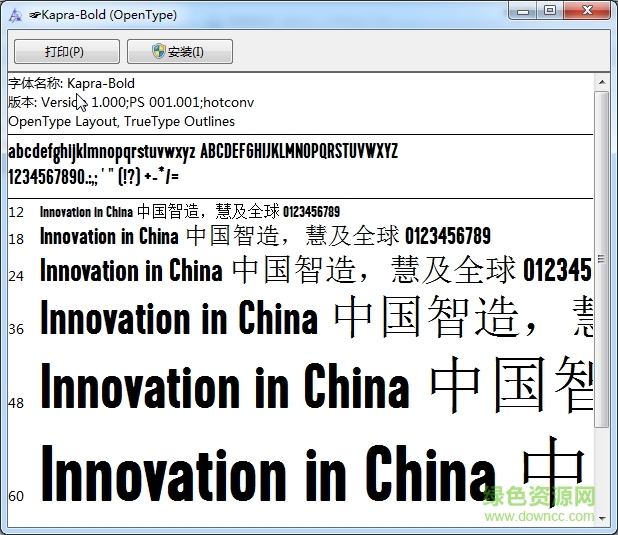
kapra bold是一款粗黑端正的英文字體,讓英文有不一樣的藝術展現(xiàn)方式,給人大氣莊嚴的厚重感,如果你有嚴肅主題或內(nèi)容,可以來綠色資源網(wǎng)試試這款字體!
kapra bold是kapra系列字體的黑體,整體色彩飽滿造型纖長,給你威嚴聳立的視覺體驗,可以廣泛運用與藝術設計、海報設計、名片設計等場合!